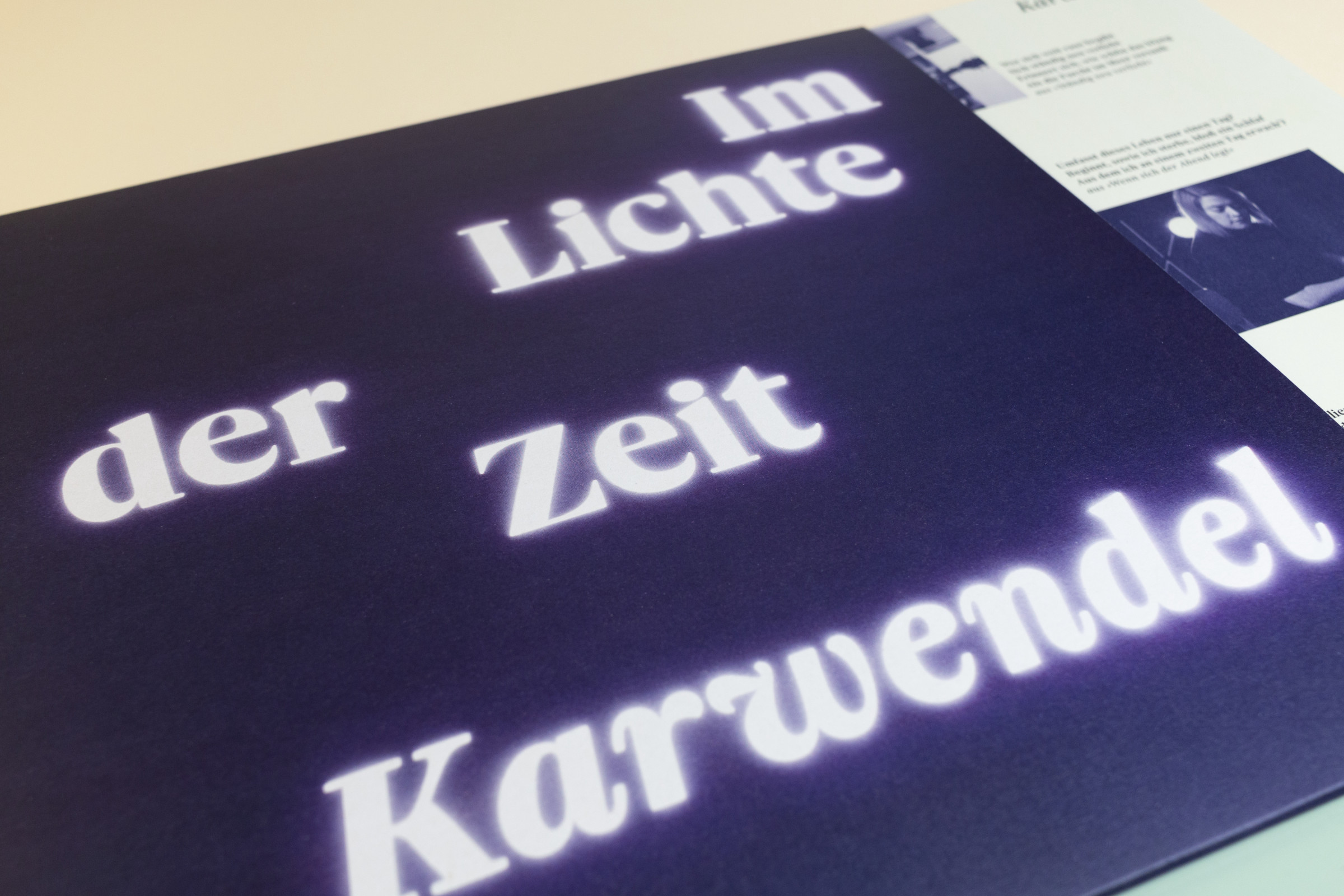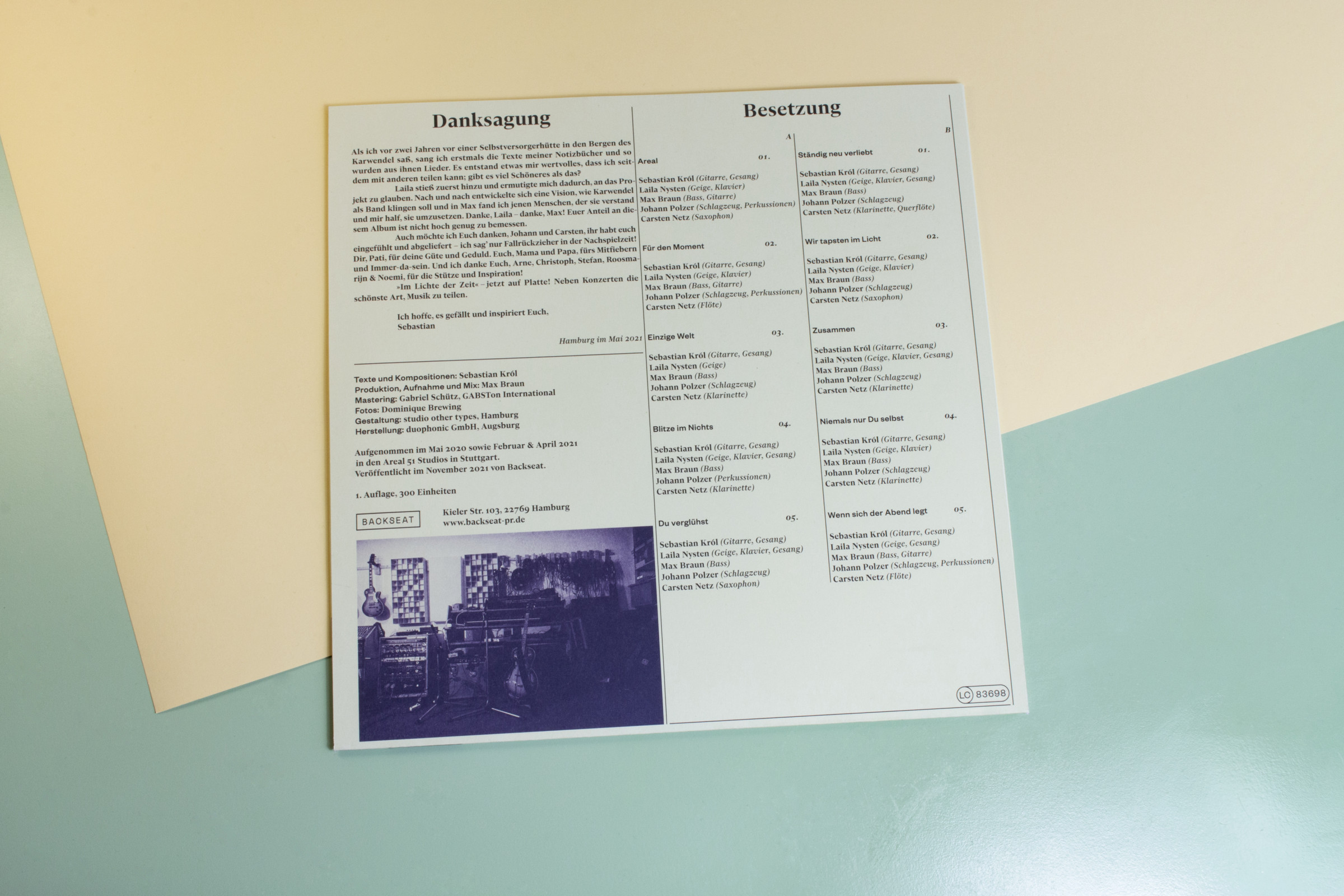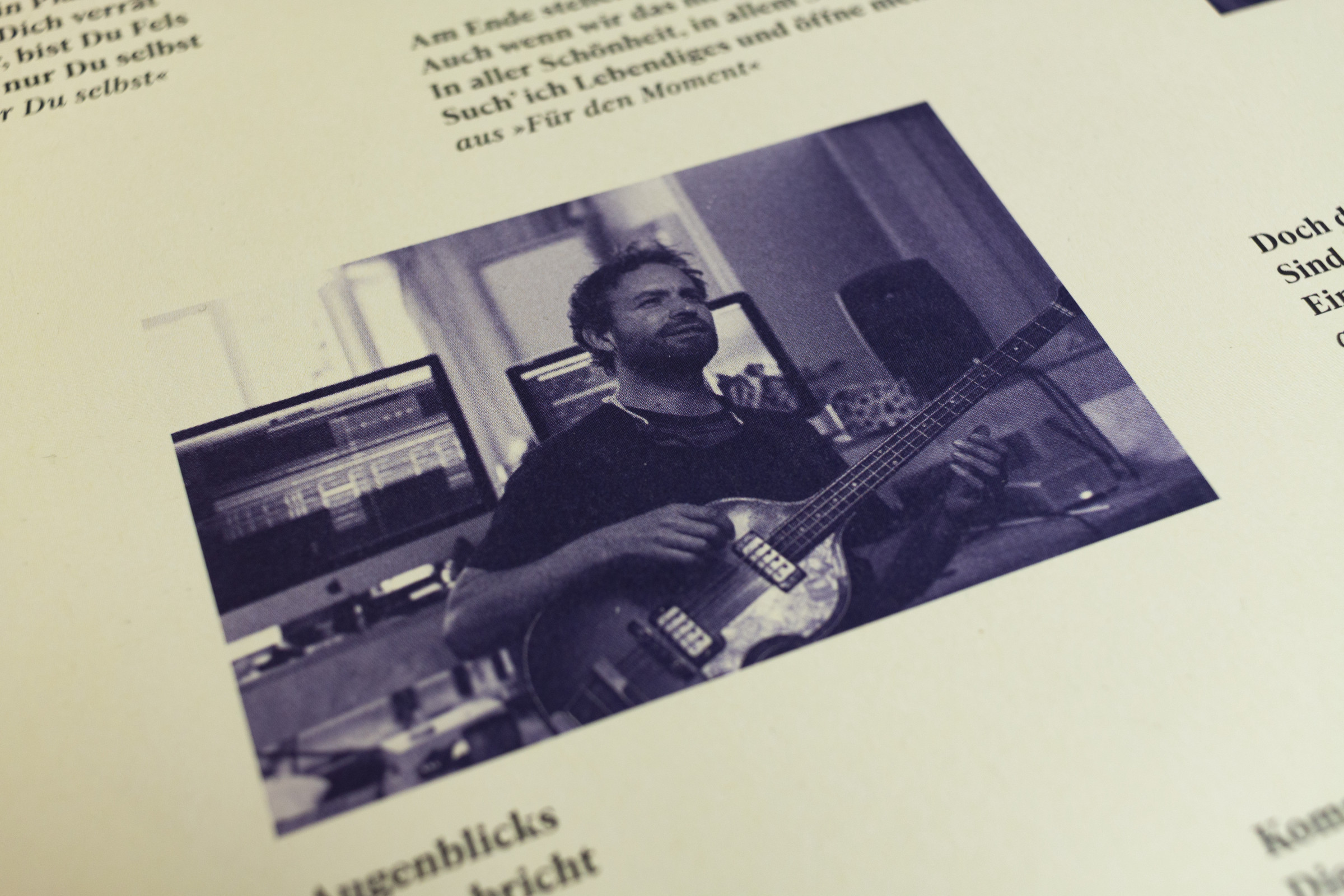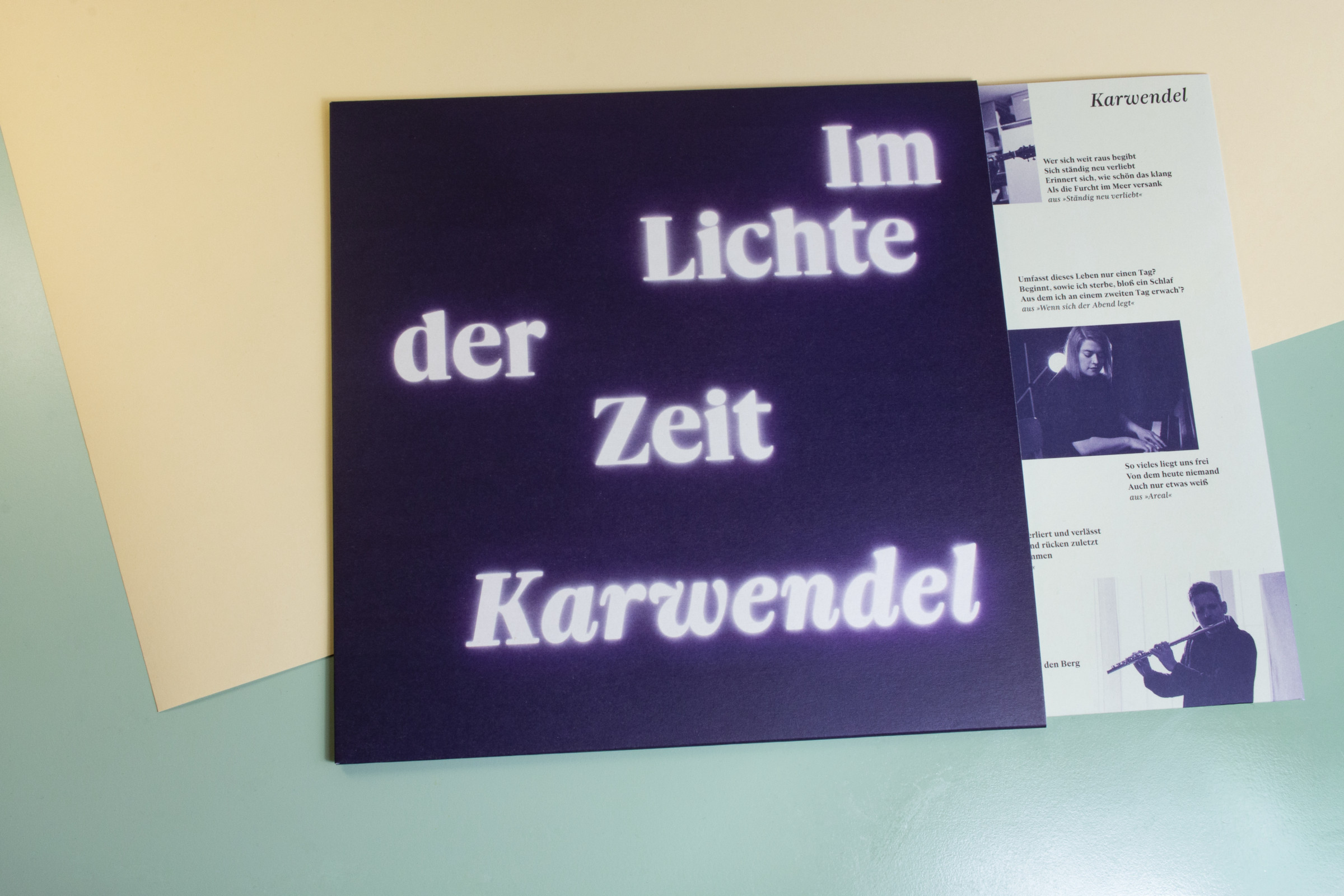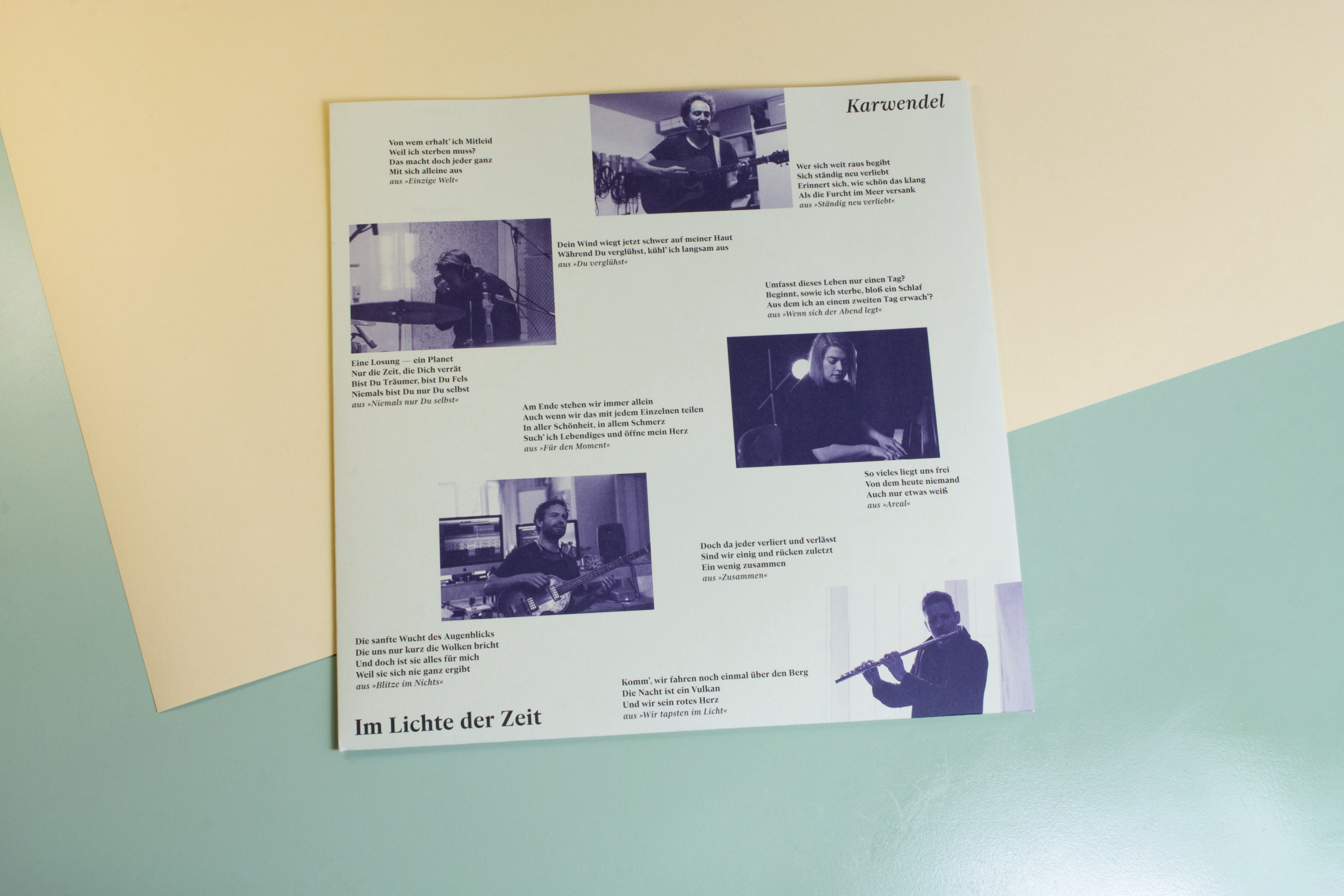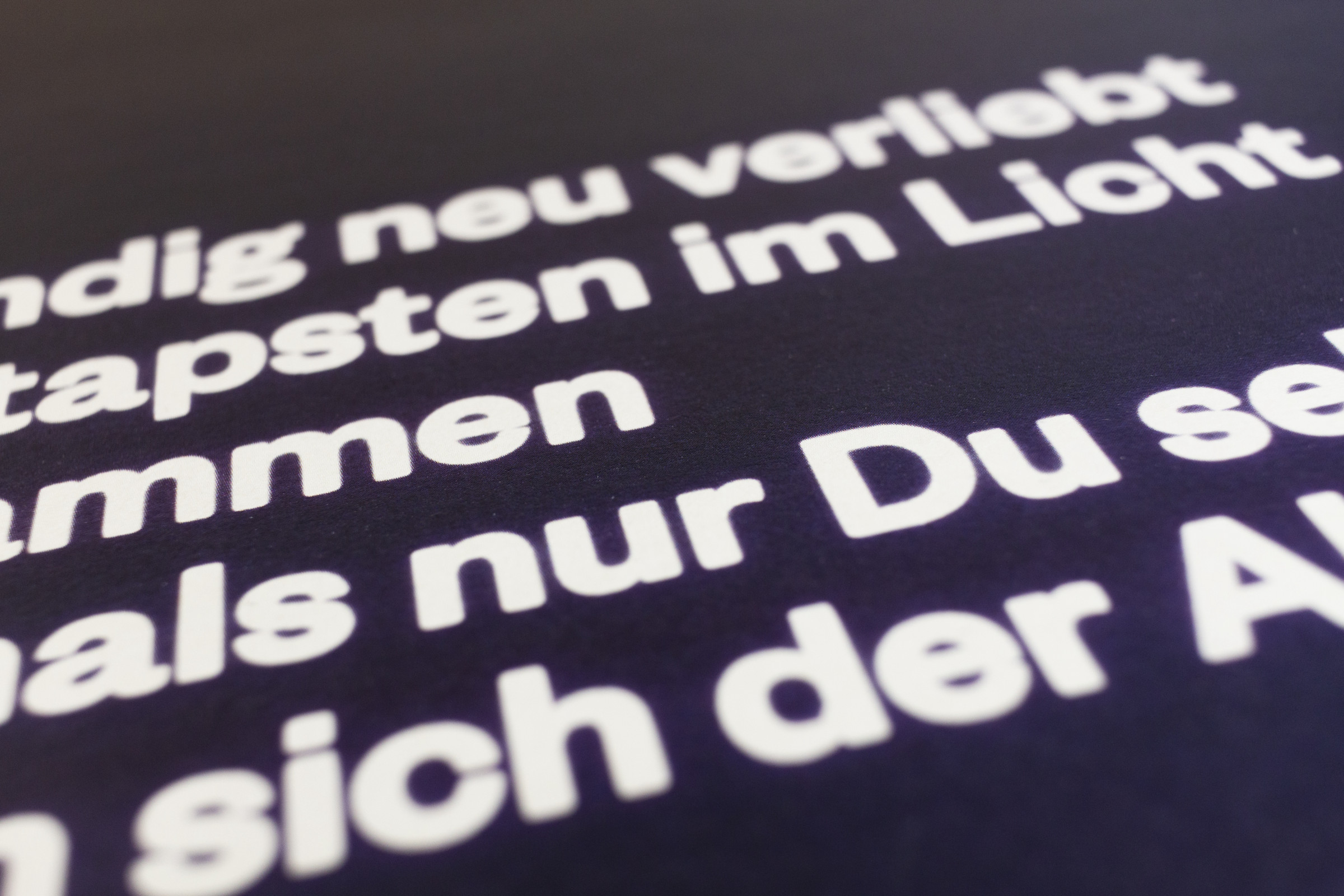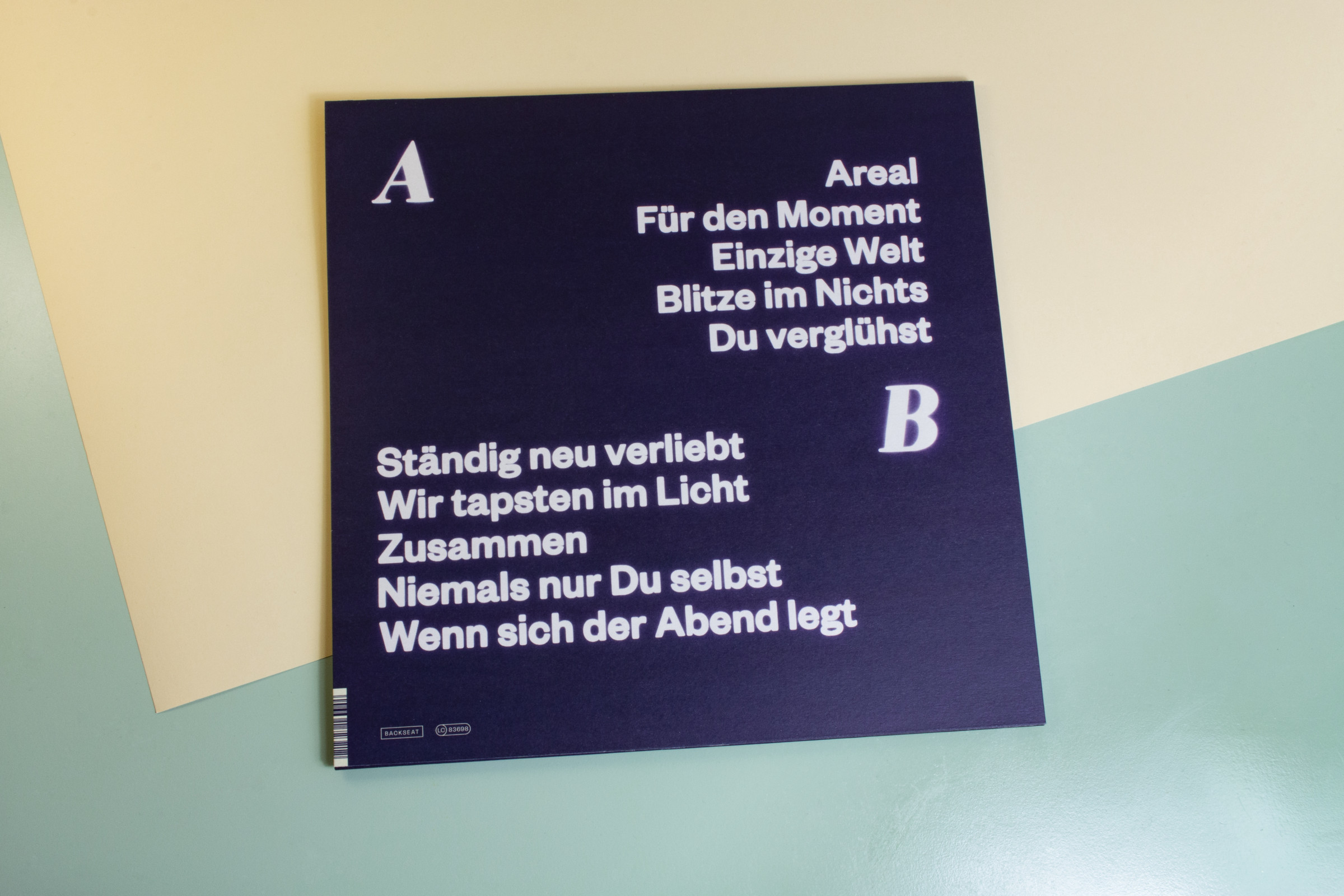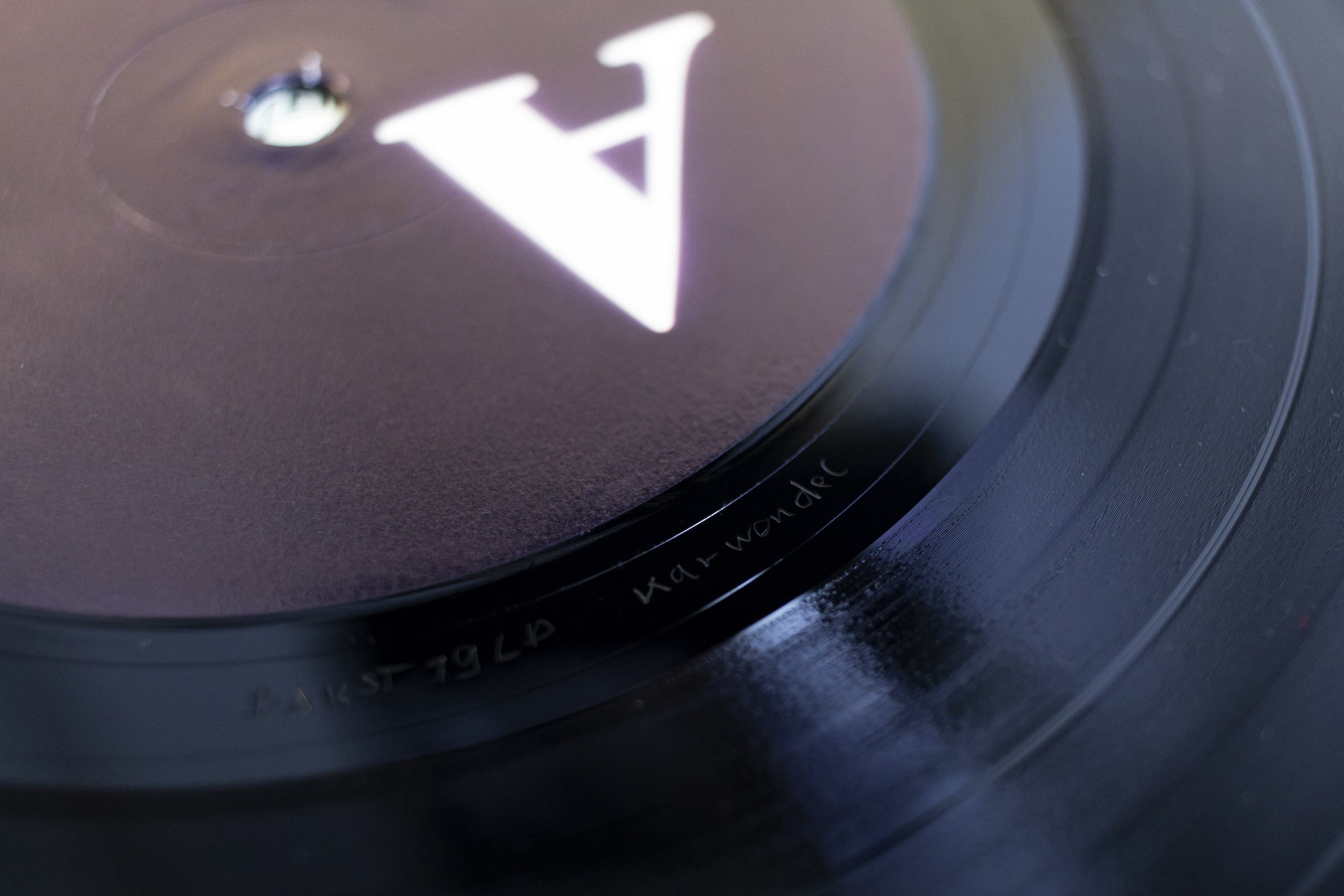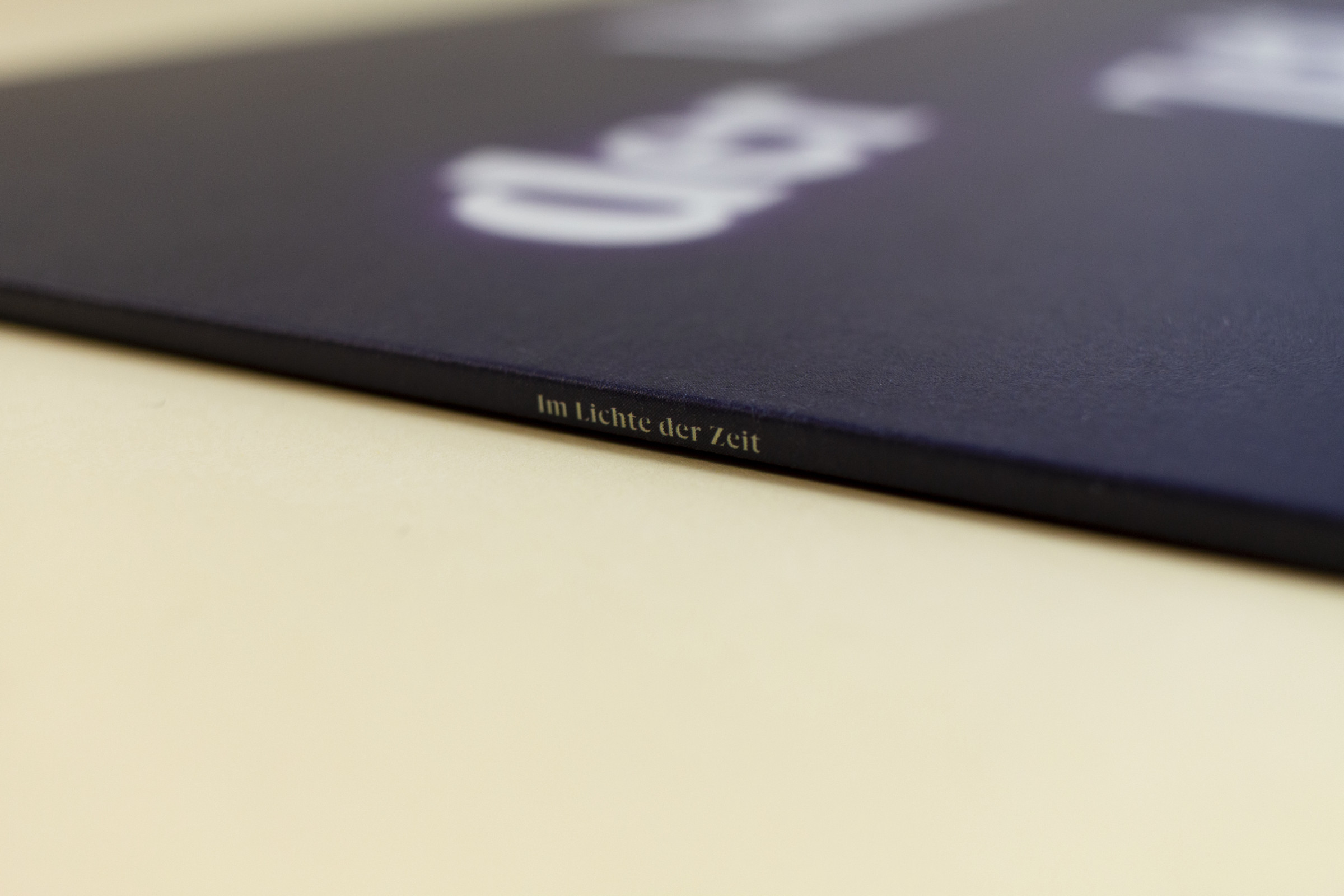
Im Lichte der Zeit
Karwendel ist ein Singer-Songwriter aus Hamburg. Die Titelgestaltung auf dem Cover ist in einem analogen Prozess mithilfe des Lichts eines Scanners entstanden. So enstanden diffuse Buchstaben, die die ephemere Klangwelt des Albums widerspiegelt.
Schrift: Founders Grotesk von Klim Type Foundry
& Gliko Modern von R-Typography